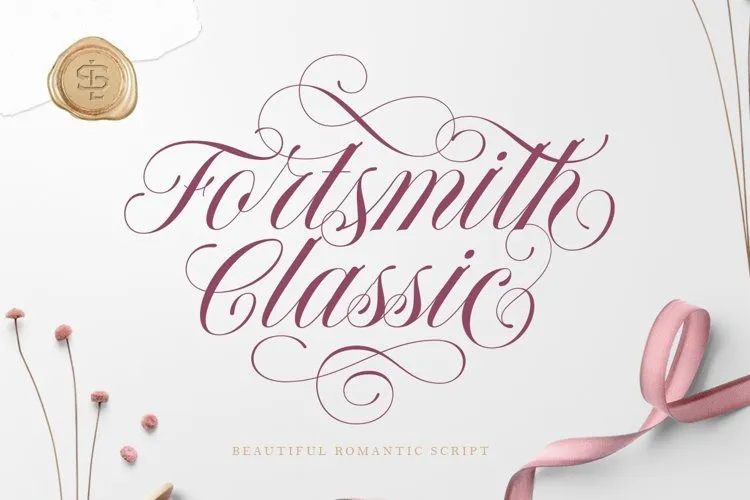
Forth Smith Font – Fonte Grátis
Forth Smith Font
A fonte Forth Smith é uma escolha perfeita para quem valoriza uma escrita elegante e sofisticada. Com sua aparência limpa e moderna, ela se destaca como uma opção ideal para design gráfico e letras decorativas. Seu estilo sensual e glamouroso complementam designs de qualquer gênero. O fato de ter múltiplos alternantes estilizados oferece flexibilidade para criar diferentes efeitos, enquanto os swashes em formato EPS fornecem um toque sofisticado e detalhado. A Forth Smith é perfeitamente adequada para letras grandes e impactantes, como cabeçalhos ou design editorial, proporcionando uma leitura agradável sem esforço. Este font é fácil de usar, com muitos pontos de interseção elegantly projetados que tornam qualquer texto mais sofisticado. Não importa se você está trabalhando em um projeto de design de marca, gráficos publicitários ou até mesmo uma composição artística – a Forth Smith vai deixá-lo impressionado com sua capacidade de capturar o olhar e criar textos impressionantes. É importante mencionar que este é um recurso para designers e criadores de conteúdo que valorizam leitura fluída e estética sofisticada. Combinando elegância, facilidade de leitura e estilo próprio, a Forth Smith pode transformar o seu trabalho em algo realmente especial.